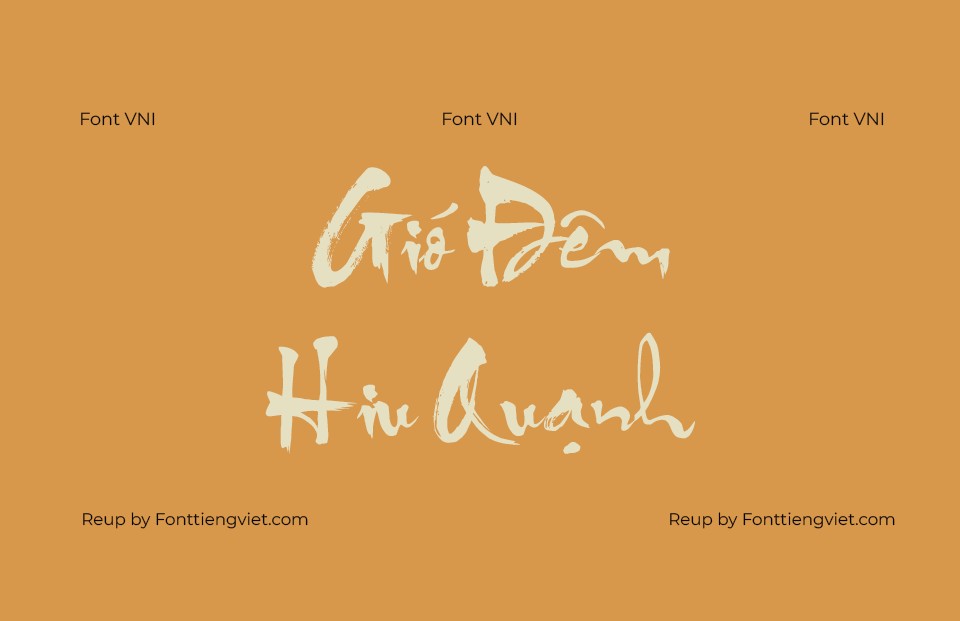
Trong thế giới thiết kế đồ họa và soạn thảo văn bản, việc lựa chọn một Font Chữ đẹp và phù hợp là yếu tố then chốt tạo nên sự chuyên nghiệp và thu hút. Đối với người dùng Việt Nam, đặc biệt là học sinh, sinh viên và các nhà thiết kế cần sự chuẩn xác về tiếng Việt, bộ Font Việt hoá VNI HLThupap đã trở thành một lựa chọn không thể thiếu. Đây không chỉ là một phông chữ thông thường, mà còn là sự kết hợp hoàn hảo giữa nét đẹp thư pháp truyền thống và khả năng tương thích cao với các bộ gõ tiếng Việt phổ biến. Phông chữ này mang đến sự tinh tế, rất được ưa chuộng trong việc thiết kế các ấn phẩm mang tính nghệ thuật cao, từ các bài thuyết trình học đường đến các ấn phẩm chuẩn bị cho mùa thi tốt nghiệp quan trọng.
Giới Thiệu Chi Tiết Về Font Việt hoá VNI HLThupap và Lịch Sử Phát Triển
Thuộc dòng font VNI (Vietnamese National Institute), Font Việt hoá VNI HLThupap là một trong những bộ font chữ thư pháp được yêu thích nhất. Hệ thống VNI từ lâu đã quen thuộc với người dùng Việt, nổi tiếng với sự ổn định và khả năng hiển thị đầy đủ các dấu tiếng Việt mà không gặp lỗi. Sự “Việt hóa” ở đây đảm bảo rằng mọi ký tự đặc biệt, dấu câu và các biến thể chữ cái đều được thể hiện chính xác theo chuẩn tiếng Việt hiện đại. Cái tên “HLThupap” gợi lên tính chất thư pháp (Thư Pháp – TP) của font, với những nét uốn lượn mềm mại, mang đậm tính nghệ thuật. Việc sử dụng font này giúp các bài viết, các poster thông báo hoặc thiệp mời trở nên trang trọng và độc đáo hơn, rất phù hợp cho các sự kiện của trường học hoặc lễ tốt nghiệp.
Đặc Điểm Nổi Bật và Lý Do Được Ưa Chuộng
Sức hấp dẫn của Font Việt hoá VNI HLThupap nằm ở sự kết hợp hiếm có giữa tính nghệ thuật và tính ứng dụng thực tiễn.
- Tính Thư Pháp Độc Đáo: Font mô phỏng nét viết tay mềm mại, uyển chuyển của nghệ thuật thư pháp truyền thống Việt Nam, tạo cảm giác gần gũi và giàu tính thẩm mỹ.
- Việt Hóa Hoàn Chỉnh: Đảm bảo hiển thị hoàn hảo các ký tự có dấu, tránh tình trạng lỗi font hay mất nét thường gặp ở các font quốc tế không được tối ưu hóa. Đây là yếu tố then chốt cho mọi tài liệu học thuật và văn bản chính thức.
- Phù Hợp Với Giáo Dục: Nhiều giáo viên và học sinh lựa chọn font này để thiết kế tiêu đề bài giảng, chứng nhận khen thưởng hoặc các tài liệu học tập yêu cầu tính trang trọng, đẹp mắt.
Ứng Dụng Thực Tiễn Trong Lĩnh Vực Học Đường và Thiết Kế Ấn Phẩm Quan Trọng
Từ góc độ trường học và sinh viên, Font Việt hoá VNI HLThupap có nhiều ứng dụng thiết thực. Ví dụ, trong các sự kiện kỷ niệm ngày Nhà giáo Việt Nam, font này thường được dùng để thiết kế thiệp mời hoặc bằng khen, tạo nên sự trang trọng cần thiết. Đối với các bạn học sinh cấp 3 chuẩn bị cho các bài thi cuối cấp hoặc dự án khoa học, việc sử dụng một font chữ nổi bật nhưng vẫn dễ đọc như thế này giúp thu hút sự chú ý của giám khảo và nâng cao chất lượng trình bày tổng thể.
Trong thiết kế chuyên nghiệp, đặc biệt là in ấn lịch Tết, banner quảng cáo sự kiện văn hóa hoặc các ấn phẩm mang phong cách cổ điển, font chữ thư pháp này luôn là ưu tiên hàng đầu. Khả năng tùy biến linh hoạt và bộ ký tự phong phú giúp nhà thiết kế dễ dàng tạo ra các tác phẩm độc đáo. Nhiều chuyên gia SEO cũng khuyến nghị sử dụng các font việt hóa chất lượng cao để đảm bảo rằng nội dung trực tuyến hiển thị chuẩn xác, tránh các lỗi kỹ thuật làm giảm trải nghiệm người dùng.
Việc sở hữu bộ font này sẽ mở ra nhiều cánh cửa sáng tạo cho bạn, dù bạn là sinh viên, giáo viên, hay nhà thiết kế đồ họa chuyên nghiệp. Đây là một công cụ không thể thiếu để tạo ra các tài liệu chuẩn tiếng Việt với tính thẩm mỹ cao.
Tóm lại, Font Việt hoá VNI HLThupap là một tài sản quý giá trong kho tàng Font Chữ của bất kỳ người dùng nào làm việc với nội dung tiếng Việt. Từ những nét thư pháp mềm mại, uyển chuyển cho đến khả năng việt hóa hoàn chỉnh, font chữ này đáp ứng mọi yêu cầu khắt khe về mặt thẩm mỹ và kỹ thuật. Việc tối ưu hóa việc sử dụng các font việt hóa chất lượng cao như VNI HLThupap không chỉ giúp tăng tính chuyên nghiệp của sản phẩm mà còn góp phần bảo tồn và phát huy vẻ đẹp của chữ viết tiếng Việt. Nếu bạn đang tìm kiếm sự hoàn hảo cho dự án học thuật, thi cử, hay bất kỳ thiết kế nào đòi hỏi sự tinh tế, đừng ngần ngại tải và trải nghiệm ngay bộ Font Việt hoá VNI HLThupap tuyệt vời này. Đây chính là chìa khóa để bài viết của bạn trở nên nổi bật và ấn tượng hơn bao giờ hết.